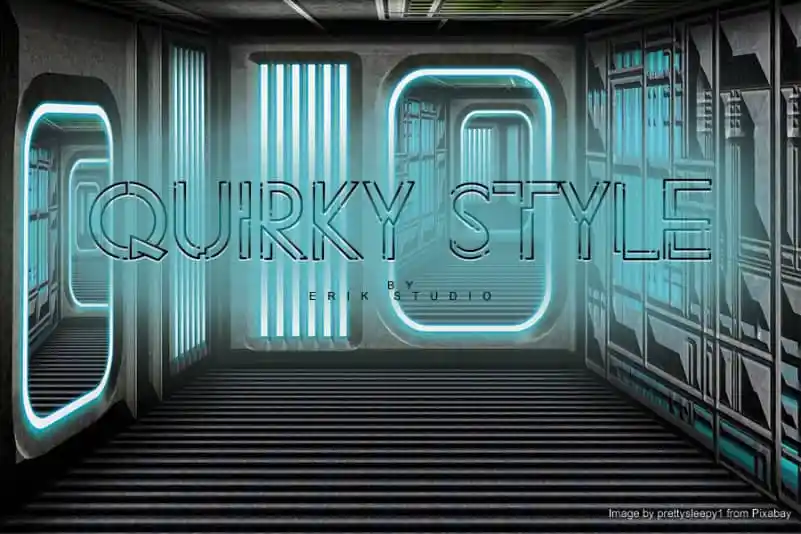
Quirky Style Display Font – Fonte Grátis
Quirky Style Display Font
A ‘Quirky Style Display Font’ é uma fonte display vibrante e única que traz a frescura de um estilo contemporâneo aos seus projetos. Esta fonte irá dar ao seu design uma cara nova, tornando suas ideias criativas mais chamativas e destaca-as em meio à multidão. Seja para criar um site elegante ou montar um layout de newsletter atraente, adicione esta fonte inovadora aos seus planos e observe o impacto que ela faz em suas criações. Não deixe de explorar a vasta gama de possibilidades que essa fonte oferece, já que cada letra carrega consigo uma personalidade única. Com ‘Quirky Style Display Font’, seu trabalho gráfico ganha um toque inovador e irreverente sem perder a elegância necessária em projetos mais formais.